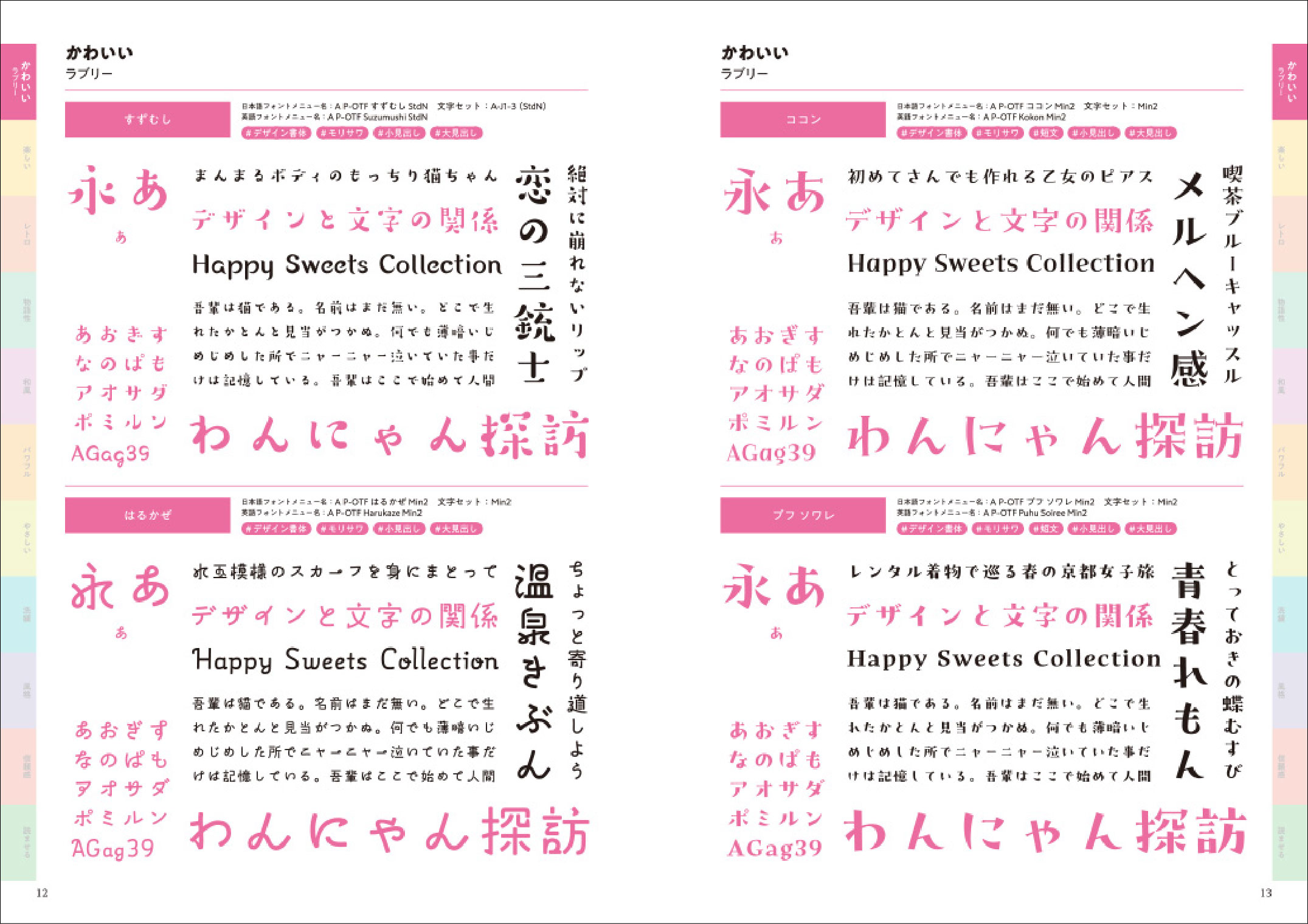
「表現・特徴で見つけるフォントBOOK Morisawa Fonts書体見本帳2024–2025」
「Morisawa Fonts書体見本帳」のコンセプト
実際にユーザーが書体を探すシーンを考慮し、より最適な書体にアクセスしやすく、各書体の個性を活かした使い分けができるように3つの検索方法を採用しています。検索方法を複合的に使いながら目的の書体を探すことで、より制作物にマッチした書体が直感的に見つかります。
1.「つくりたい表現で探す」
「かわいい」「レトロ」「物語性」「パワフル」など、表現したい作風やイメージにマッチする11種類のキーワードから探すことができます。書体の使用シーンを彷彿とさせる組見本によって、ライブラリーの世界観を楽しみながら書体を見つけることができます。
2.「特徴で探す」
「ペン字・手書き」「コンデンス」「教育用」など、形や仕様、用途といった具体的な特徴から関連する書体同士を比較できます。細分化された書体ジャンルによって、制作物に合った特徴を持つ書体を探すことができます。
3.「全書体見本」
2,000書体を超えるMorisawa Fontsのライブラリーを、書体分類・ブランドに基づいて網羅的に一覧できます。
豪華な巻頭特集や役立つTipsを収録
特集企画では、大幅追加となった2024年度新書体の一部を使用して、四季それぞれのシーンをフォントで表現したグラフィック作例を掲載。個性的な新書体たちの雰囲気を味わいながら、デザイン制作のヒントにしていただけます。また、Morisawa Fontsの便利な使い方やUD(ユニバーサルデザイン)書体の解説、文字セットといった基本情報のほか、OpenType機能を使った字形の切り替え、カーニング設定など、役立つTips記事も掲載しています。